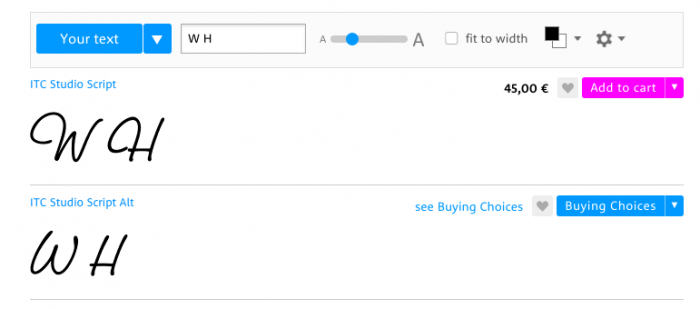
Suche vergebens die Schriftart von dem Bild
Ich suche schon seit Tagen den Namen einer Schriftart. Bis jetzt aber leider erfolglos :(
Obwohl das große W und H etwas anderes aussehen...